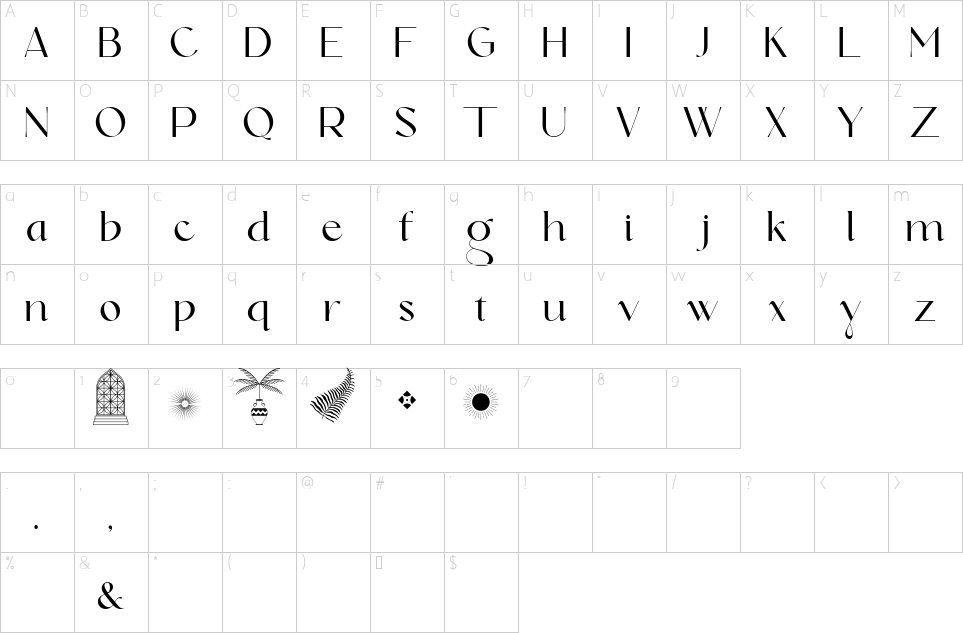
Descubra Dolce And Amyara Font, uma elegante fonte gratuita para Windows e Mac, criada por Pudu Dody Permana. Este design único se destaca com linhas suaves e harmoniosas, ideal para estilos modernos de design gráfico. Com características refinadas, esta fonte é perfeita para aplicativos digitais e projetos em impressão que valorizam uma aparência sofisticada e elegante. Gratuito para download, Dolce And Amyara oferece um leque amplo de opções de estilo, permitindo-lhe explorar a diversidade do design. Com o tempo, sua fonte pode tornar-se parte integrante de seu portfólio, fornecendo uma variação única que diferencie seus projetos em meio à multidão. Seja para criar materiais digitais ou impressos, Dolce And Amyara é a escolha perfeita para quem procura um design moderno e elegante sem comprometer as condições de uso.